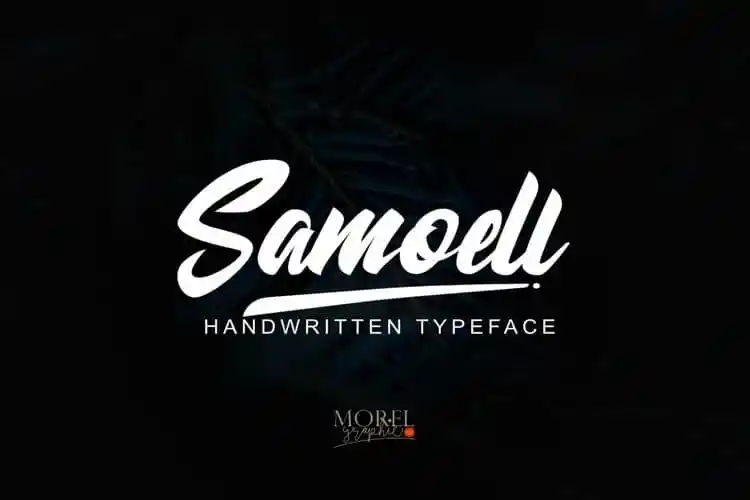
Samoell Script Font
Introduzimos a Samoell Script Font, uma tipografia script com traços ágeis e rústicos. Este tipo de letra é perfeitamente adequada para criar logos e logotipos, rótulos, frases de citação, embalagens de produto, materiais promocionais, mídia social e cartões de cumprimento. Além disso, oferece um conjunto completo das letras minúsculas e maiúsculas, caracteres alternativos, uma ampla gama de pontuação, números e suporte multilíngue. A Samoell Script Font inclui também uma variedade de caracteres alternativos que foram agrupados em várias características OpenType. Estas podem ser categorizadas como Alternativas estilísticas, Conjuntos alternativos estilísticos e Ligaturas. Essa característica única torna a fonte ainda mais versátil e atraente para um amplo espectro de aplicabilidades, desde design gráfico até criação de materiais digitais. Com sua versão multilingue, a Samoell Script Font se destaca como uma excelente opção para projetos internacionais. Agora que você sabe mais sobre a fonte Samoell Script, está pronta para explorar as possibilidades criativas!